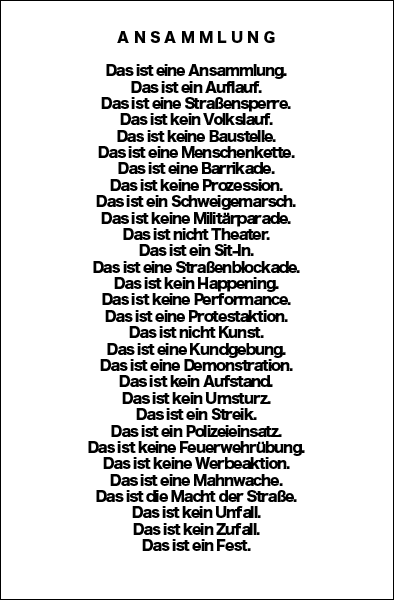
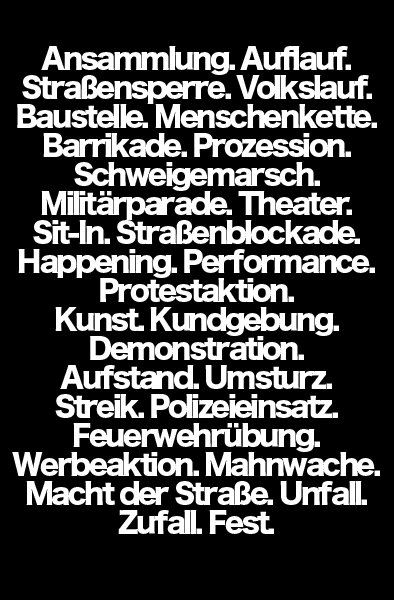
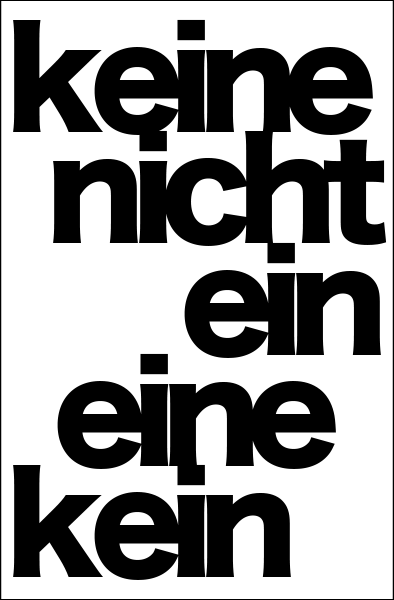
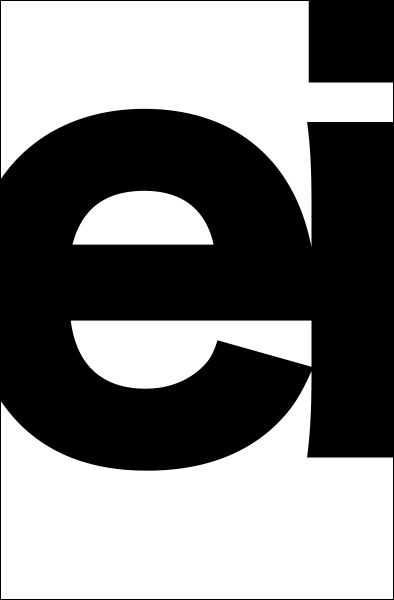
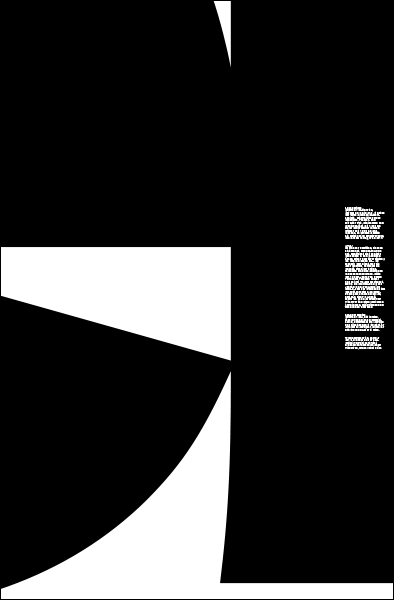
Hiragino ist eine der Schriften, die man einfach hat, wenn man Apple hat. Man findet sie irgendwo ganz unten in den staubigen Ecken seiner Schriftverwaltung. Sie ist eben schon da — ob man will oder nicht. Wer sie aber ignoriert, verpasst die Chance, einen der erfolgreichsten Fonts im asiatischen Raum kennenzulernen. Mitte der 1990er-Jahre von Osamu Torinoumi, Tsutomu Suzuki und Keiichi Takada gezeichnet, wurde die Schrift Anfang des Jahrtausends von Apple als Built- in-Font fu?r MacOS und iOS gekauft. Ihre etwas ungelenke Eleganz erscheint logisch, hält man sich vor Augen, wofu?r sie geschaffen wurde: Völkerverständigung zwischen japanischen, chinesischen und lateinischen Schriften.